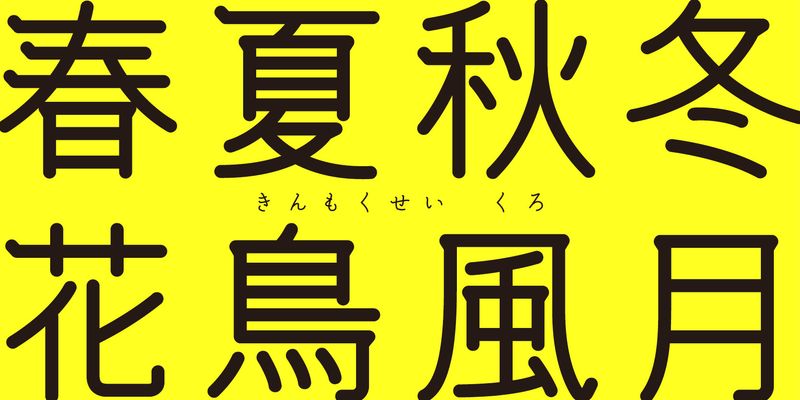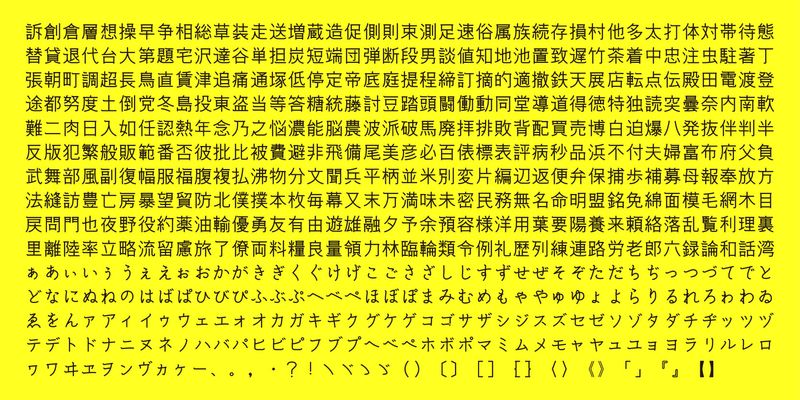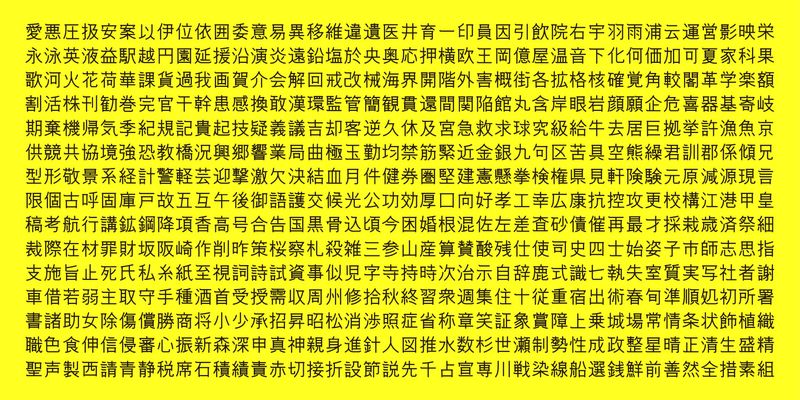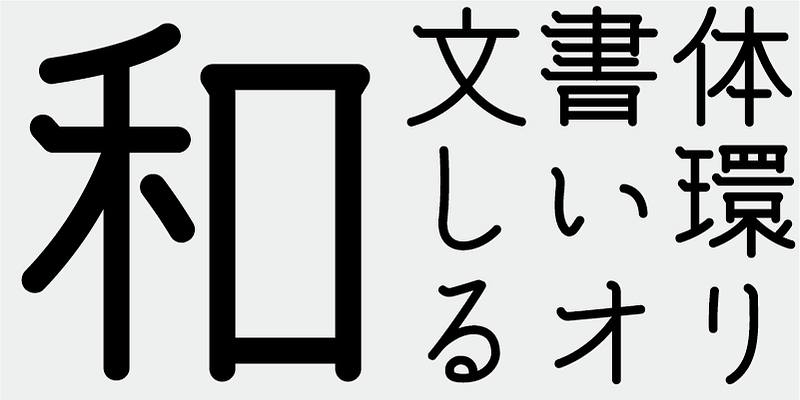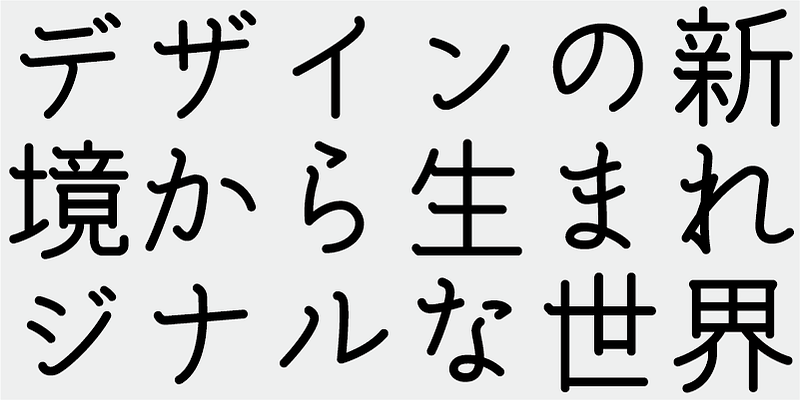
Esta é uma fonte gótica redonda desenvolvida para telas, com ênfase no início de cada traço horizontal.
Essa fonte inclui os 1.000 principais caracteres kanji escolhidos em tabelas de frequência de caracteres feitas por empresas jornalísticas, editoras e institutos de pesquisa linguística, além de 206 caracteres kana e sinais de pontuação.
Hoje em dia, na produção de fontes japonesas, os 7 mil caracteres do padrão JIS são considerados essenciais. Mas todas as fontes realmente precisam de 7 mil caracteres? Na era da fotocomposição, eram necessários muito menos caracteres. O FONT1000, um grupo de designers tipográficos independentes, começou com essa pergunta simples. Selecionamos o mínimo de mil caracteres kanji (ideogramas) necessários para a composição em japonês e criamos fontes e famílias tipográficas compatíveis. Esse conjunto de mil caracteres kanji foi selecionado usando dados de frequência de caracteres compilados por jornais, editoras, organizações de pesquisa linguística etc. Além disso, incluímos caracteres silábicos kana e sinais de pontuação. O FONT1000 foi formado em 2001 com 25 designers e 25 famílias tipográficas. Atualmente, temos 130 famílias tipográficas e contamos com quase 40 membros, tornando possível trabalhar em fontes com mais caracteres.